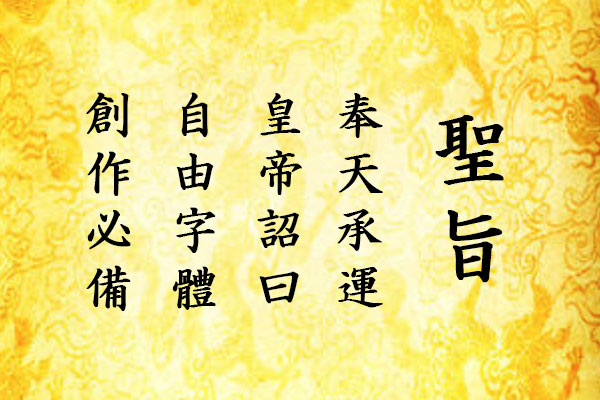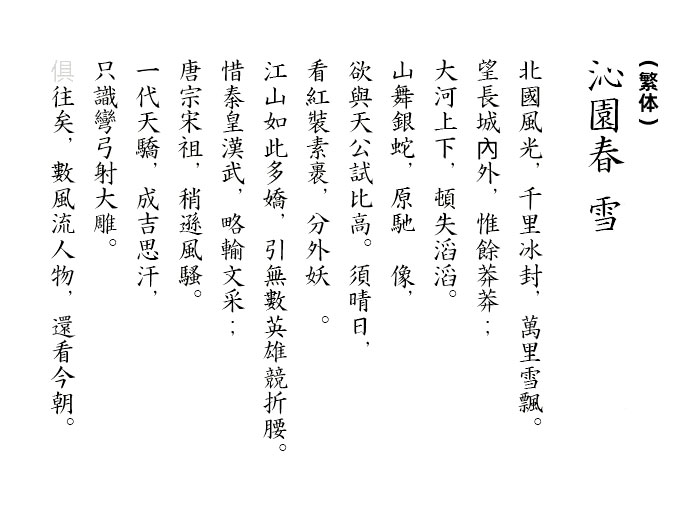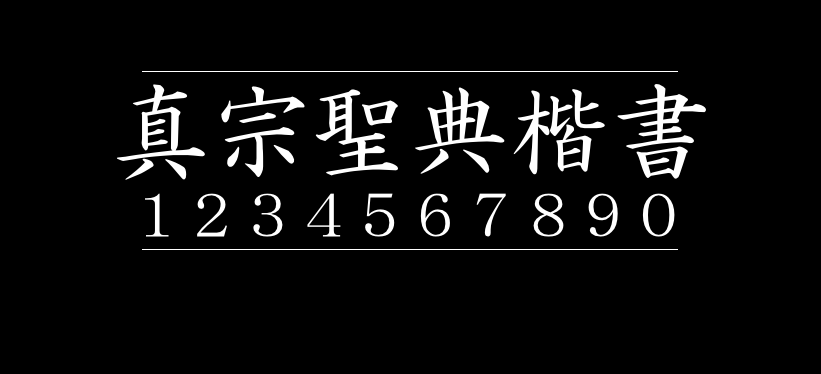
真宗圣典楷书
真宗圣典楷书(ShinshuSeitenKaisho 、真宗聖典楷書)是日本“净土真宗圣典”系列字体的其中一款,作者是日本的ARIKUNI Tomomitsu。这个字体是为了将日本佛教「净土真宗派」的各大经典电子化而开发的字体,字体字形还原原书,颇具旧时楷书风韵。
该字体繁体字符比较全,简体支持得相对少一些。